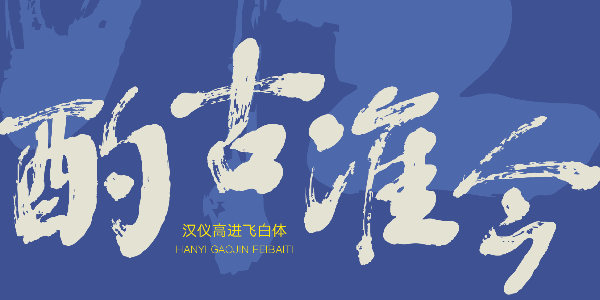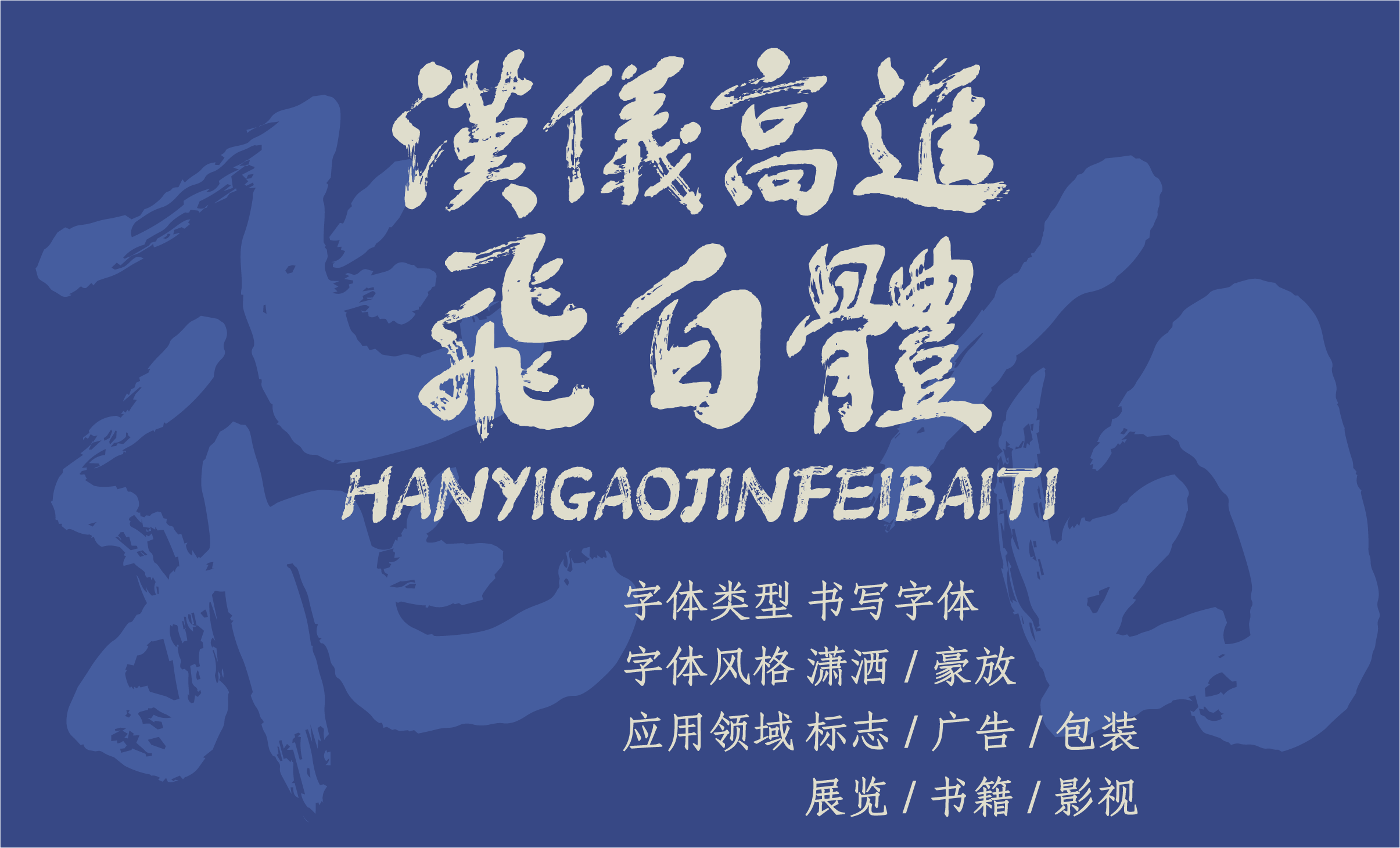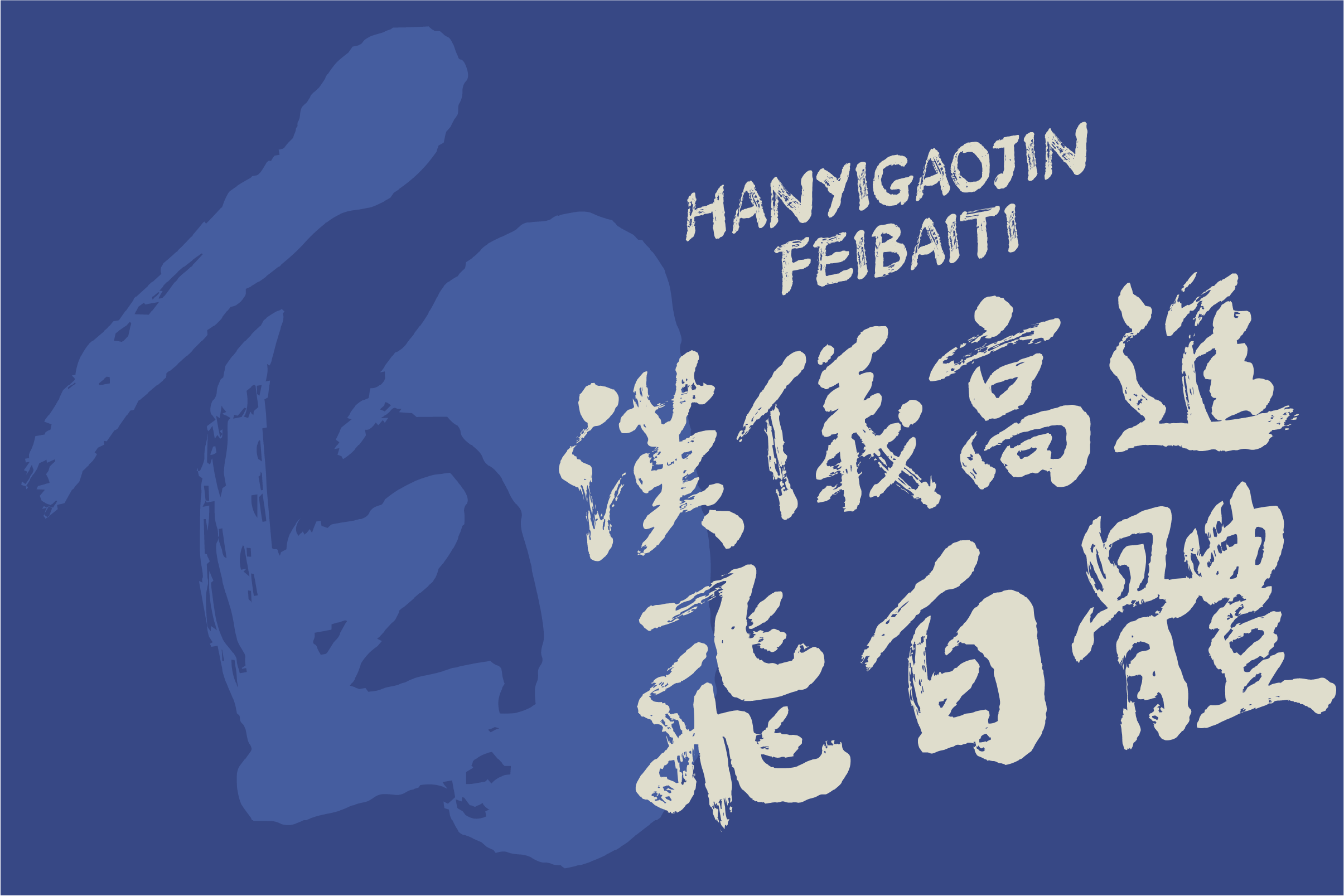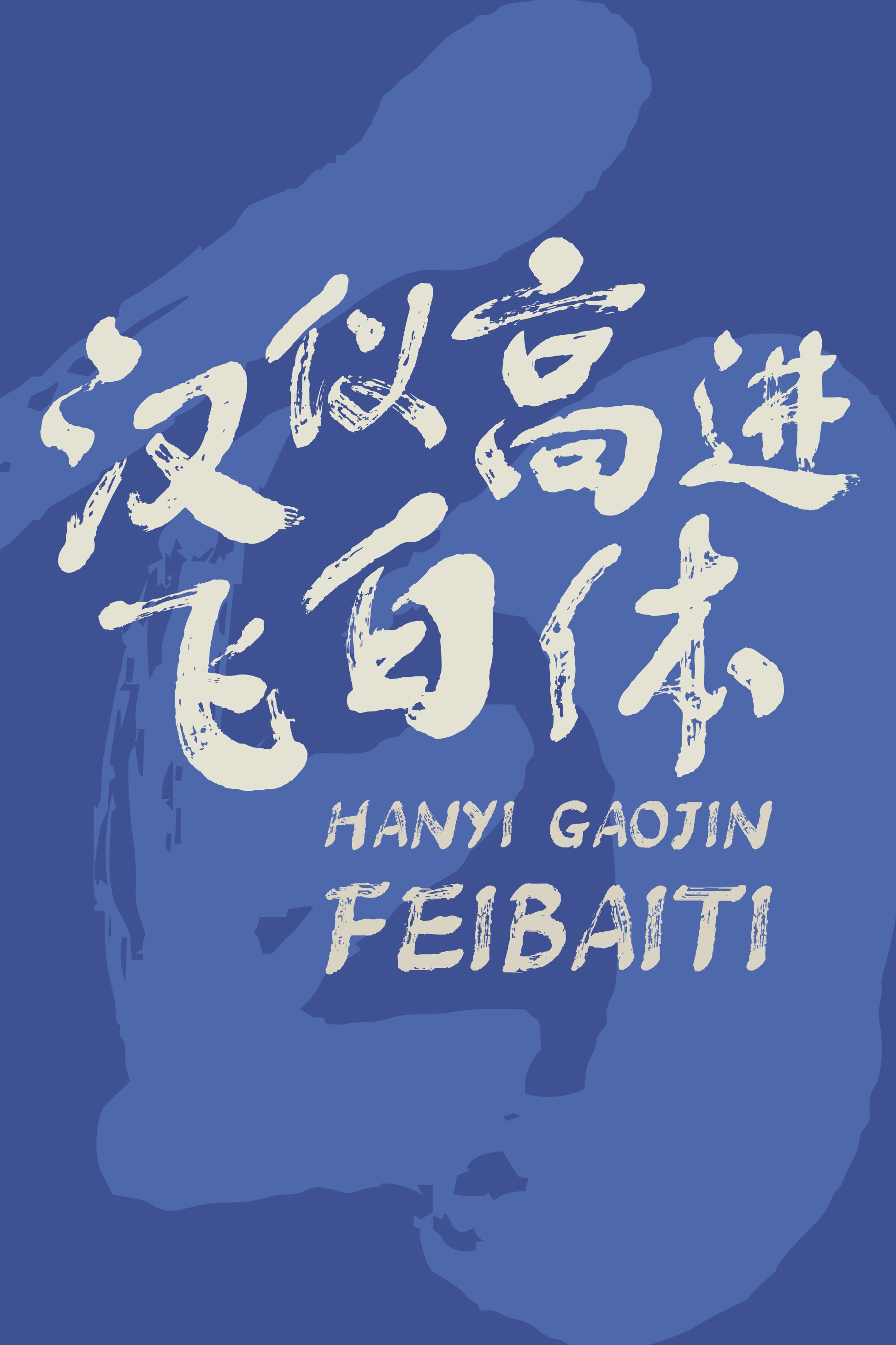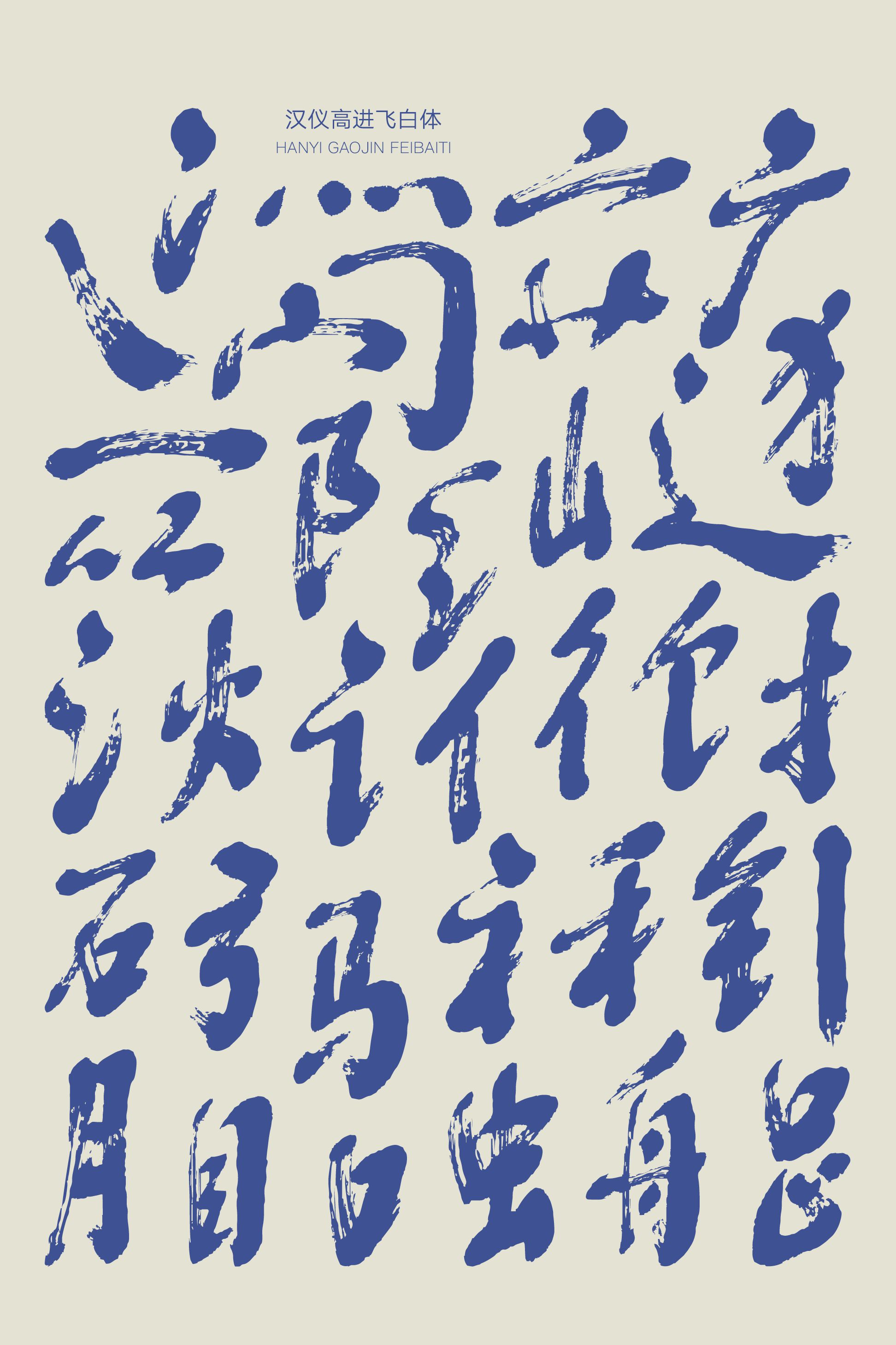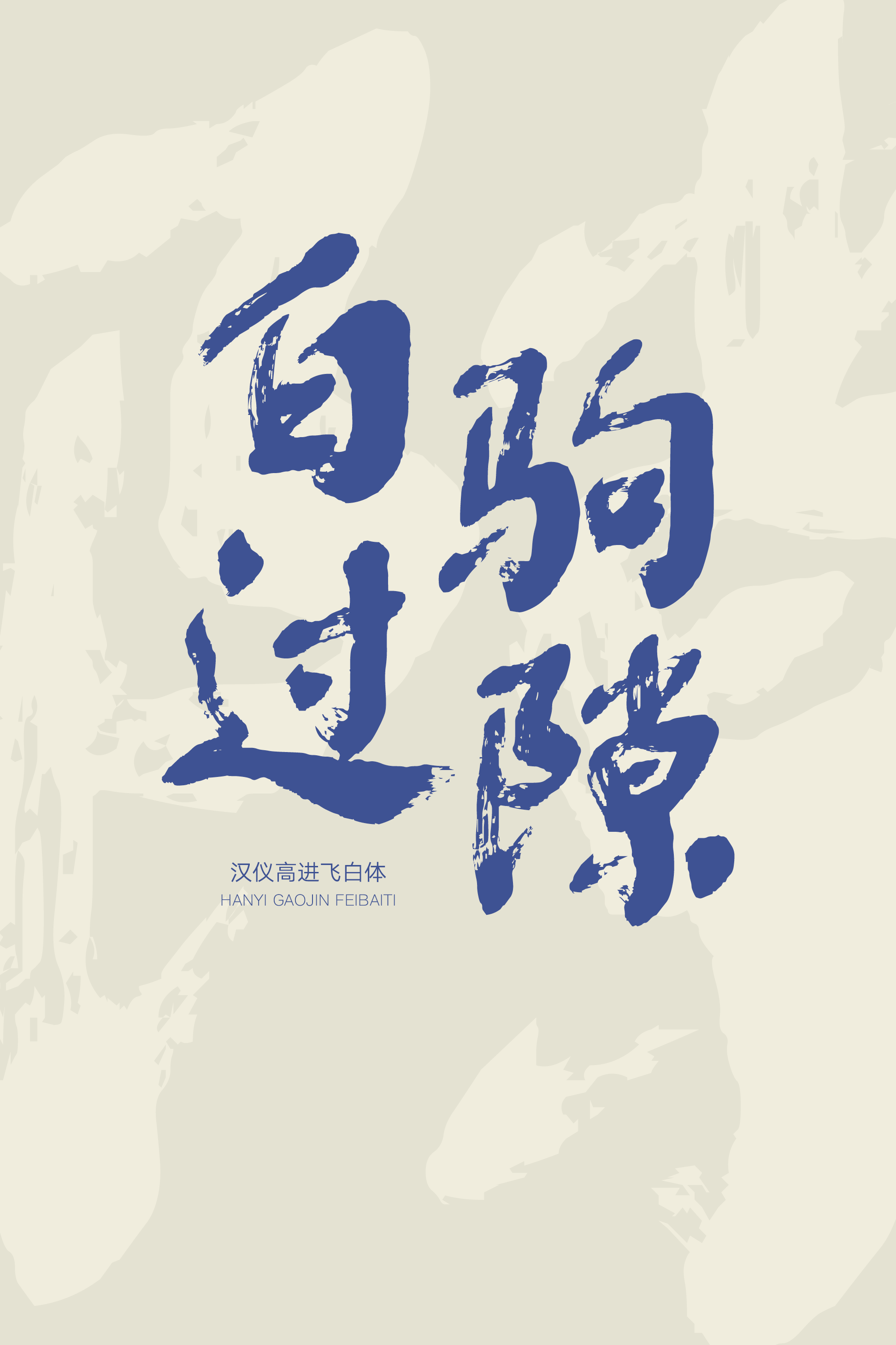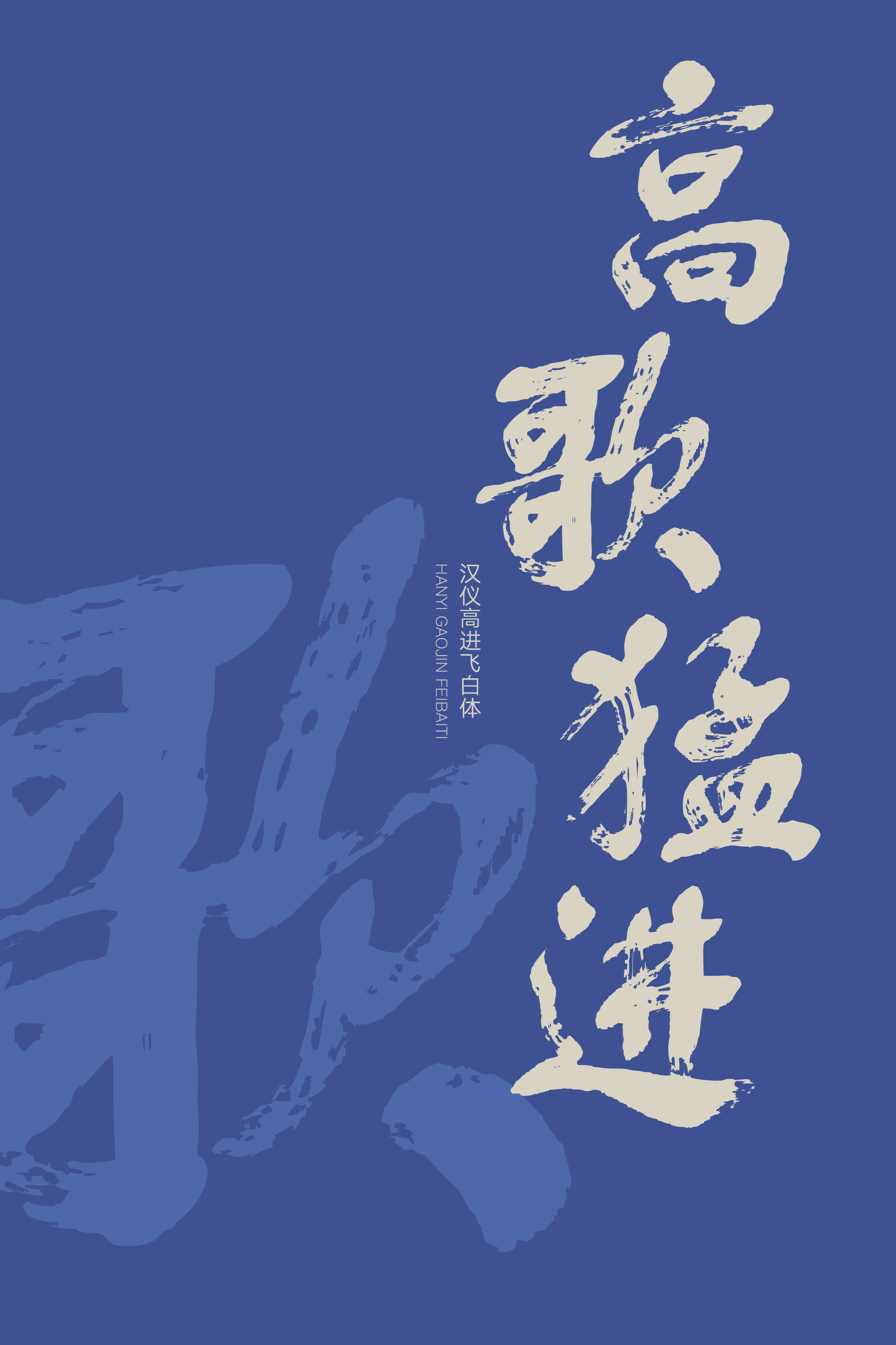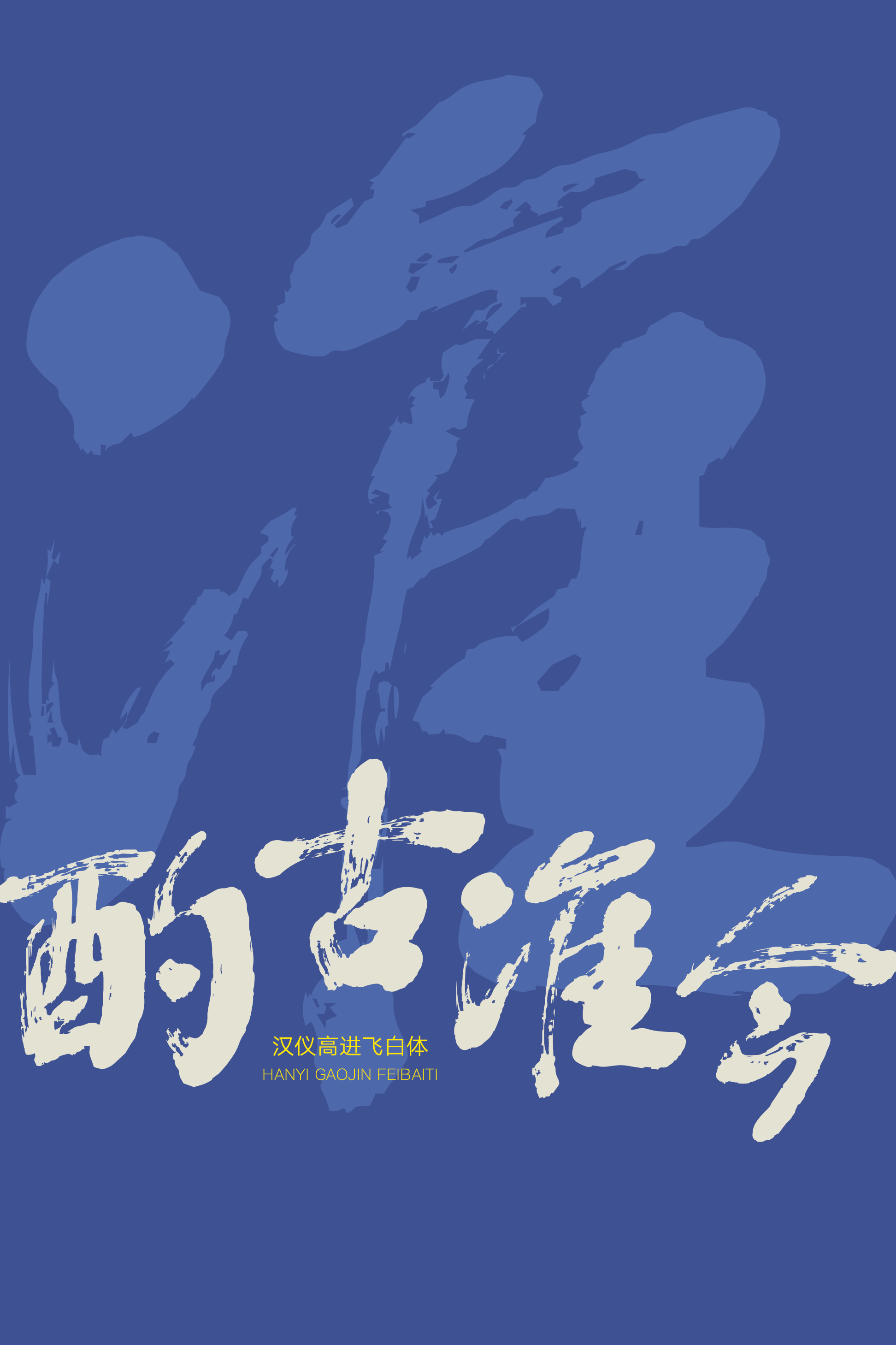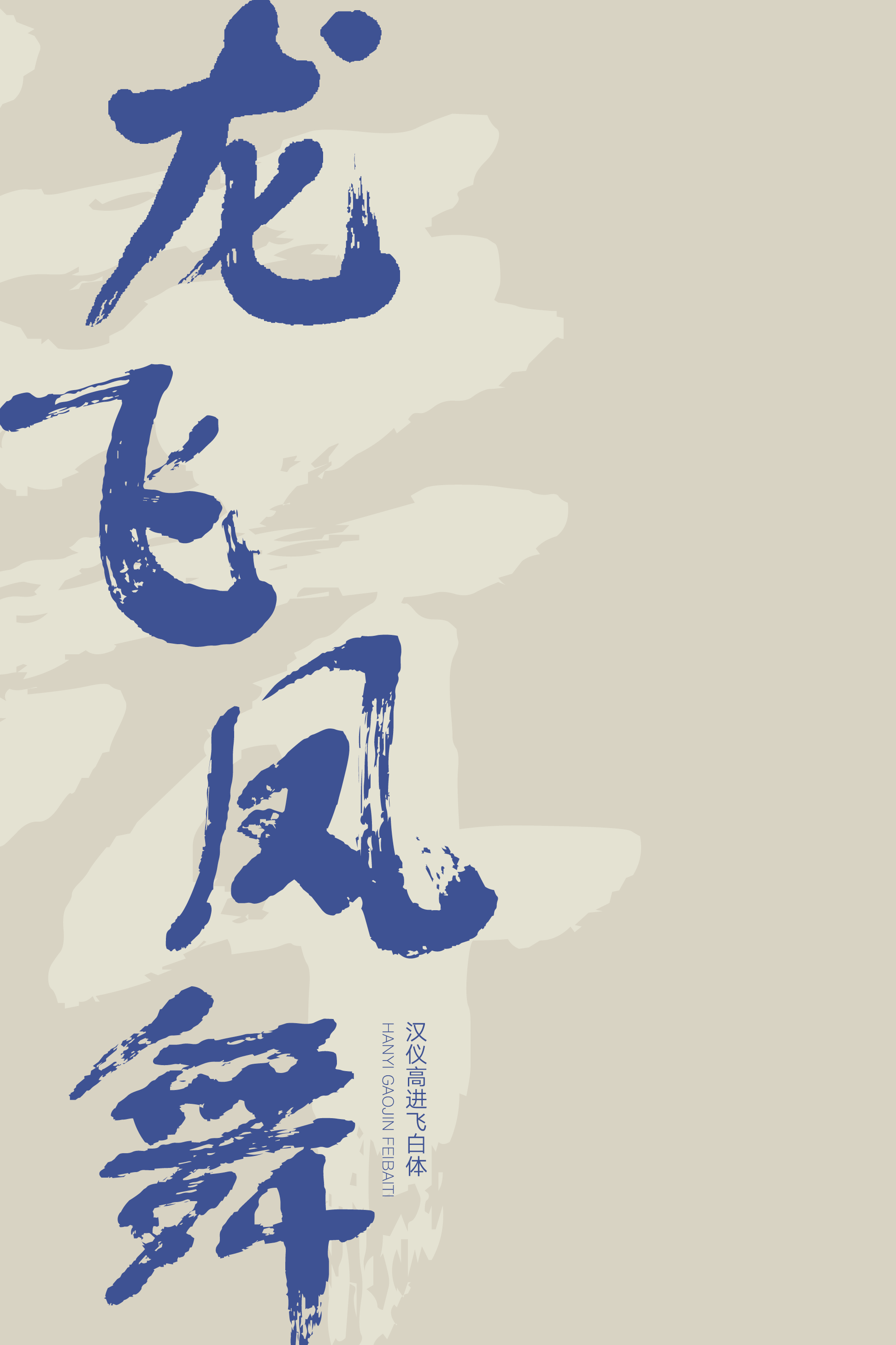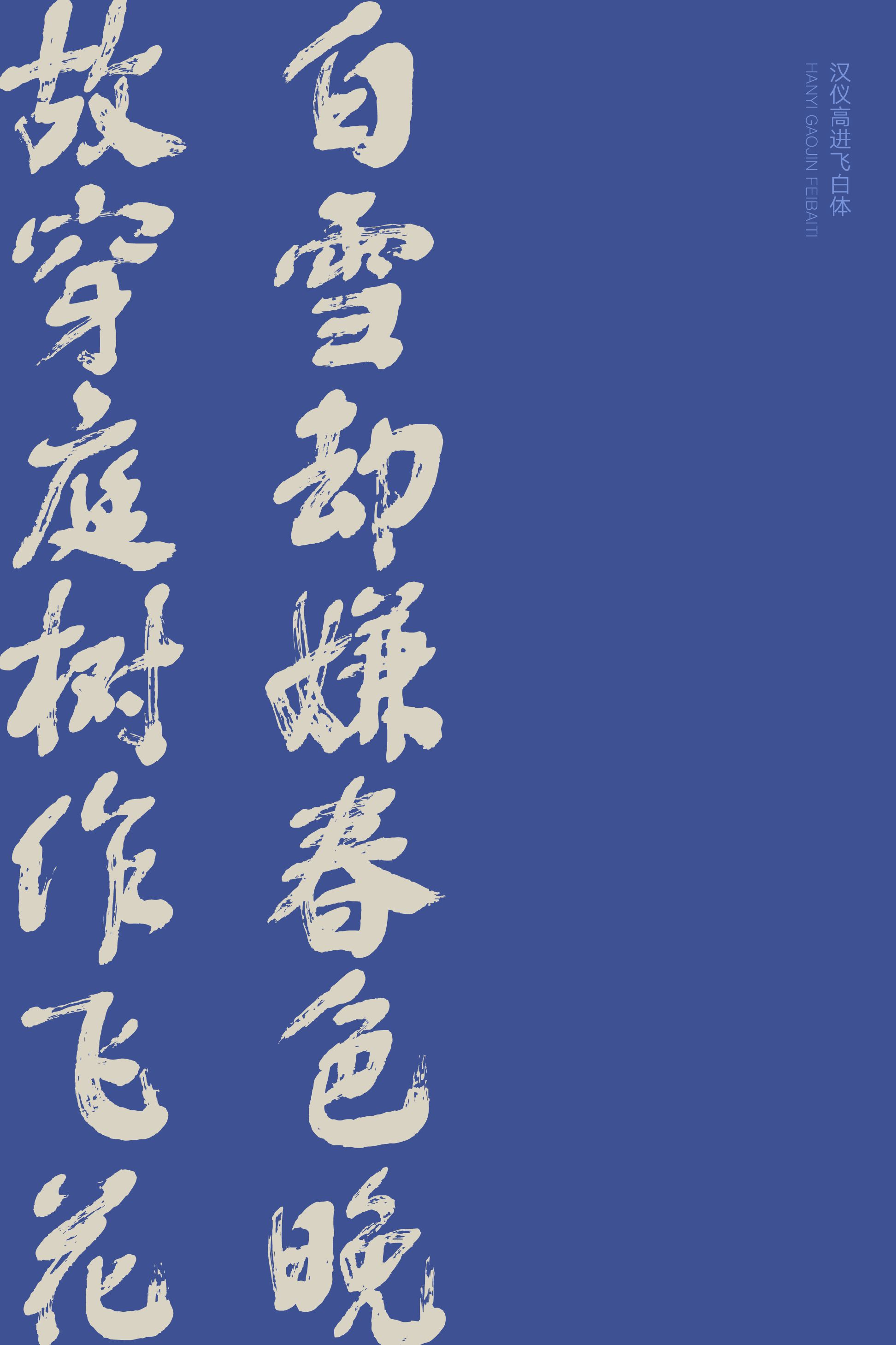
一款潇洒豪放的书写字体
汉仪高进飞白体,以行书作为基础,强调书写线条的流畅。笔势率性潇洒、行书笔意流畅。毛笔字飞白的大量运用,洋洋洒洒,使得字形整体颇具呼吸感。这款潇洒豪放的书写字体可以作为标题字体或点睛之笔,为新中式风格和国风潮流增添一丝古典气韵。
汉仪高进飞白体|字体特征
字形灵动富于变化,重心平稳。
笔画生动灵活,笔势潇洒率意。
枯笔飞白,洋洋洒洒。
西文部分同样运用了大量毛笔字飞白,西文也可见笔墨流转。
汉仪高进飞白体|字体样张